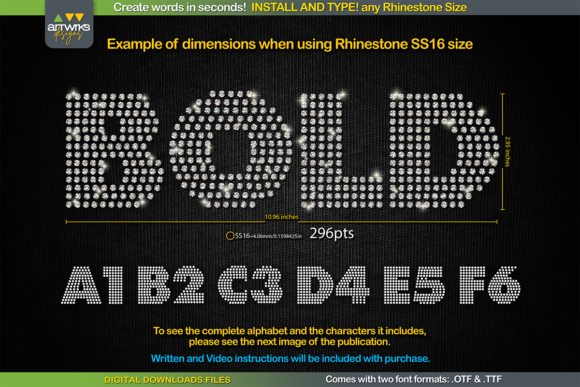
RS04 Modern DIY RHINESTONE TTF Template
RS04 Modern DIY RHINESTONE TTF Template์™€ ๊ฐ™์€ ๊ณ ํ’ˆ์งˆ ์ž์‚ฐ์„ ์ฐพ๊ณ  ์žˆ๋‹ค๋ฉด ์ด ํ”„๋ฆฌ๋ฏธ์—„ ํŒจํ‚ค์ง€๋Š” ์ฐฝ์˜์ ์ธ ํ”„๋กœ์ ํŠธ๋ฅผ ์œ„ํ•œ ํ™˜์ƒ์ ์ธ ์„ ํƒ์ž…๋‹ˆ๋‹ค.
์ •๋ฐ€ํ•˜๊ฒŒ ์ œ์ž‘๋œ RS04 Modern DIY RHINESTONE TTF Template๋Š” ๊น”๋”ํ•œ ๋ฒกํ„ฐ, ๋ถ€๋“œ๋Ÿฌ์šด ํƒ€์ดํฌ๊ทธ๋ž˜ํ”ผ ๋ฐ ์•ˆ์‹ฌํ•  ์ˆ˜ ์žˆ๋Š” ์ƒ์—…์šฉ ๋ผ์ด์„ ์Šค๋ฅผ ์ œ๊ณตํ•ฉ๋‹ˆ๋‹ค.
POD(์ฃผ๋ฌธํ˜• ์ธ์‡„) ์ œํ’ˆ, ๊ฒฐํ˜ผ์‹ ์ดˆ๋Œ€์žฅ ๋˜๋Š” ์†Œ์…œ ๋ฏธ๋””์–ด ๊ทธ๋ž˜ํ”ฝ์„ ๋งŒ๋“ค ๋•Œ RS04 Modern DIY RHINESTONE TTF Template๋Š” ์ด์ƒ์ ์ธ ์„ ํƒ์ž…๋‹ˆ๋‹ค.